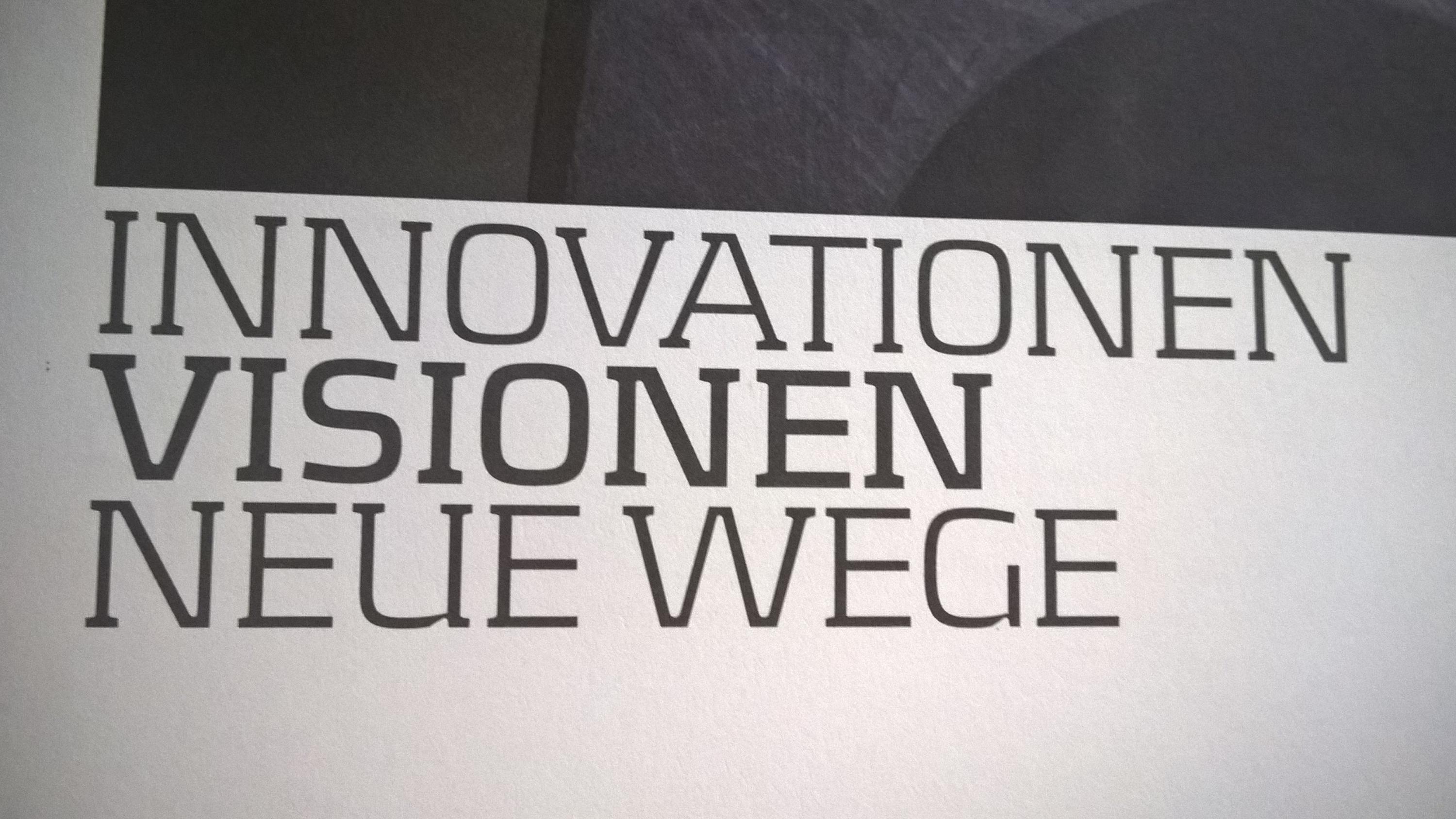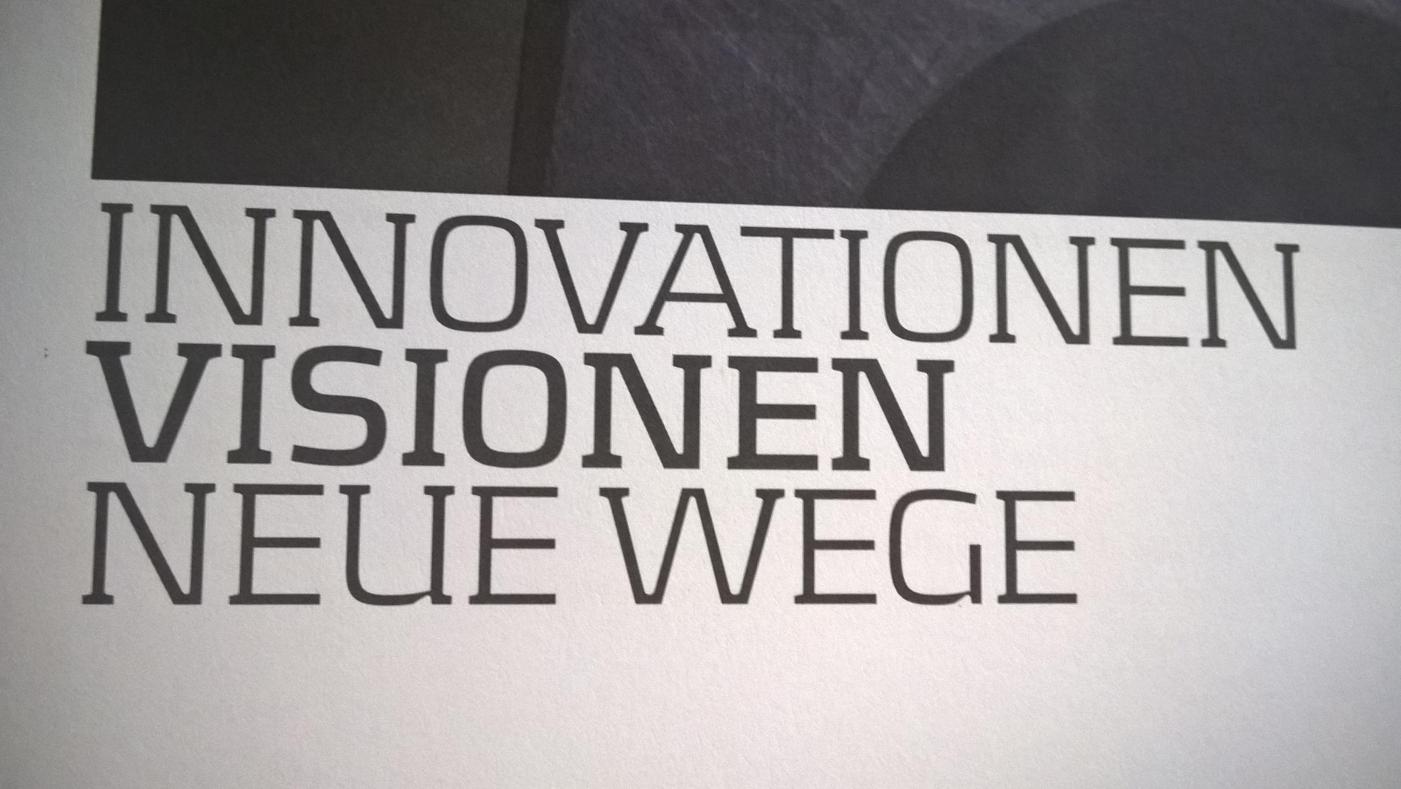
Welche Schriftart ist das? (neue Wege)
im Anhang habe ich ein Foto einer Schrift, welche ich sehr hübsch finde, jedoch absolut nicht weiss wie diese heißt und wo ich Sie mir evtl. herunterladen könnte.
Interessant sind die kleinen Verjüngungen beim U und G.
P.S. die Schrift hat Groß- und Normale kleine Buchstaben und Umlaute und soweit ich das eroieren konnte auch einige Sonderzeichnen.